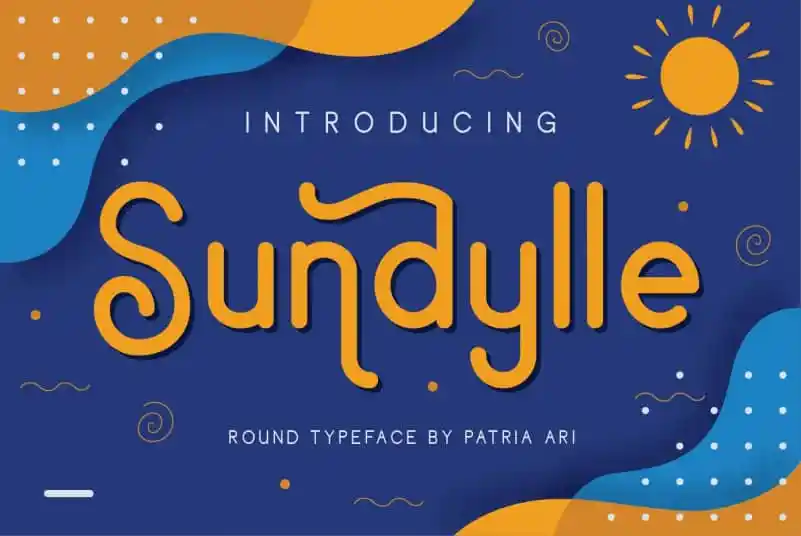
A Sundylle Sans Serif é uma tipografia sem serif que oferece características limpas com alternativas divertidas para apoiar seu projeto ou marca. Este tipo moderno e elegante combina precisão de forma com um toque leve e descontraído, criando um contraste interessante que traz uma sensação única e fresca à sua obra. Ideal tanto para gráficos digitais quanto para materiais impressos, a Sundylle Sans Serif é perfeita para projetos modernos e contemporâneos, onde você deseja criar uma atmosfera descontraída sem perder o tom proeminente de sua marca. Composta pela Patria Ari Typestudio, essa fonte é uma ótima opção para quem busca um visual clean e versátil em seus trabalhos.